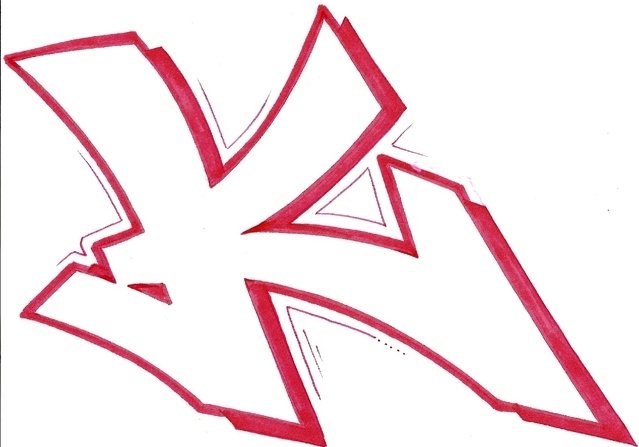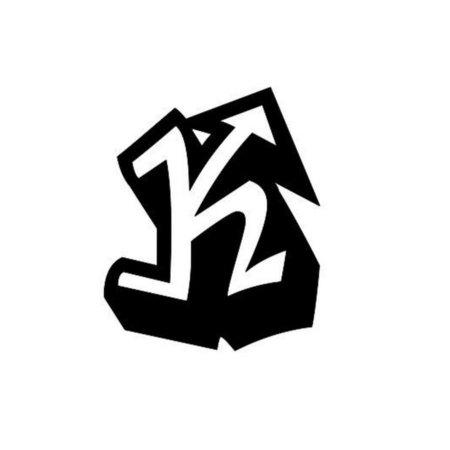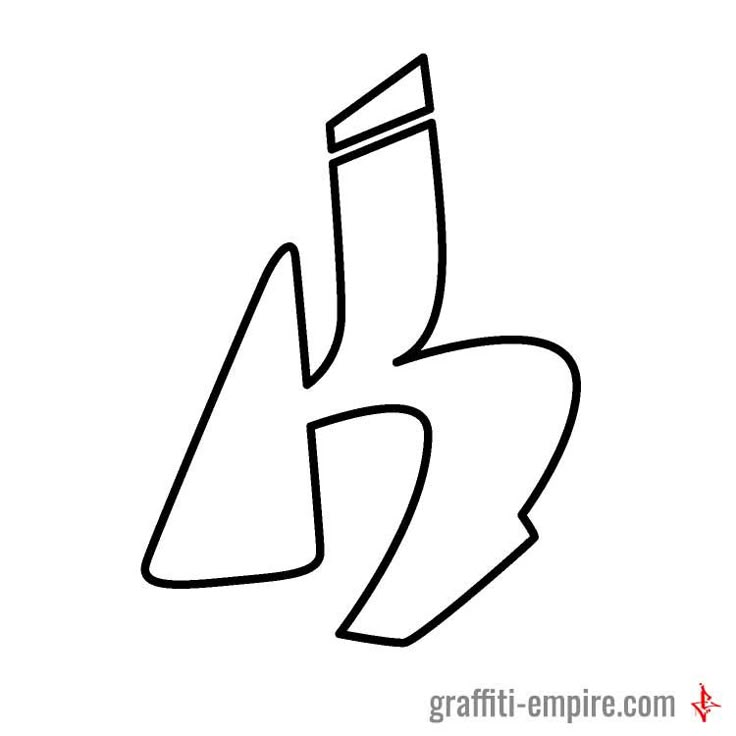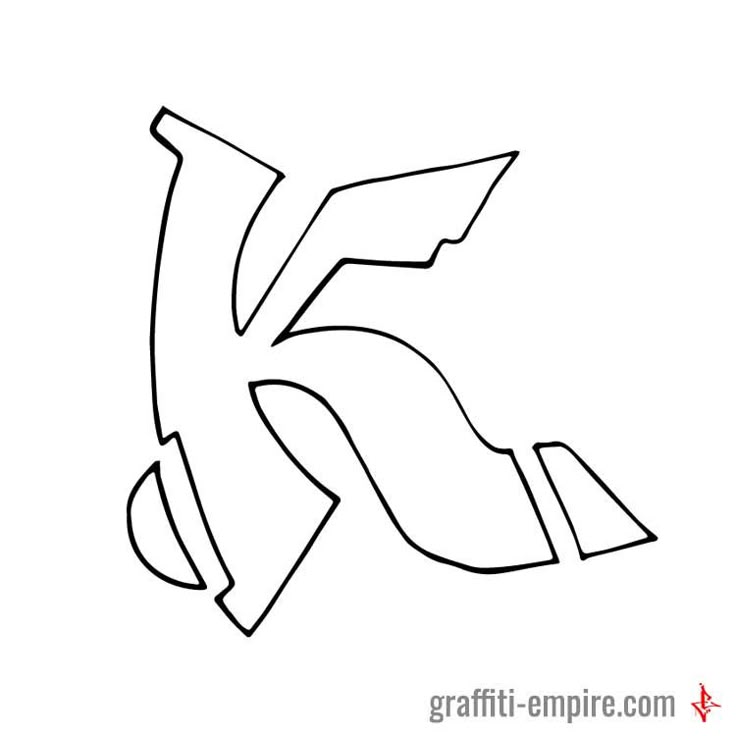
Классные картинки и рисунки буквы «К».
12 буква русского алфавита К — герой нашей сегодняшней подборки красивых картинок. Она встречается во многих словах, а в некоторых и по нескольку раз. Как и все остальные буквы в букваре, она требует тщательного изучения ребёнком, ведь пользоваться ей, он будет на протяжении всей жизни. Чтобы процесс обучения проходил легче, предлагаем в помощь карточки с буквой «К».
Пиксельный арт.
Буква в рамке.
Рисунок простым карандашом.
Карточка с буквой «К».
Срисовка для начинающих рисовать.
Вензель.
Весёлая буква «К».
В виде животного.
Жёлтая на красном фоне.
Граффити.
С глазками.
В огне.
В горошек.
Зелёная.
В золотом оформлении.
По клеточкам.
Мрачная буква.
Контурный рисунок.
Со светом.
С тенью.
В яркой короне.
Можно повторить простым карандашом.
В неоновом визуале.
Картинка в хорошем качестве.
Живая буква «К».
На фоне штриховки.
Чёрно-белая иллюстрация.
С узорами.
В разноцветном фоне.
Прикольный арт.
Рисуем по клеточкам.
Классный рисунок.
На коробке.
Картинка с буквой «К».
Маленькая картинка.
Жёлтая буква.
С огоньком
Каллиграфический почерк.
Срисовка для юных художников.
Учимся рисовать с объёмом.
Акварелью можно нарисовать что-то похожее.
Красивый рисунок.
Чёрная буква на белом фоне.
Из цветочков.
Крупным планом.
В тетрадном листе можно повторить синей ручкой.
Пытаемся украсить стандартное написание.
Граффити на стене.
Раскраска с буквой.
Маленькая и большая.
На уроке.
Буквица.
Пишем по точкам.
В свете прожекторов.
К в синем цвете.
С большими глазами.
С животным.
Для оформления.
Ч/Б.
Карточка с буквой для работы с ребёнком.
Красная.
С цветком.
В стиле поп-арт.
Контурный трафарет.
Обломки буквы.
Пишем синей ручкой.
«К» в стиле стрит-арт.
Буква светится в темноте.
С сердечками для влюблённых.
Из дерева.
В детский садик.
На урок в школу.
Объёмная буква.
Учимся рисовать вместе.
Современная картинка.
Красная буква для девочки.
Фото.
Из воздушного шарика.
На листе бумаги.
Карточка для учителя.
Для мальчика.
Повёрнутая буква «к».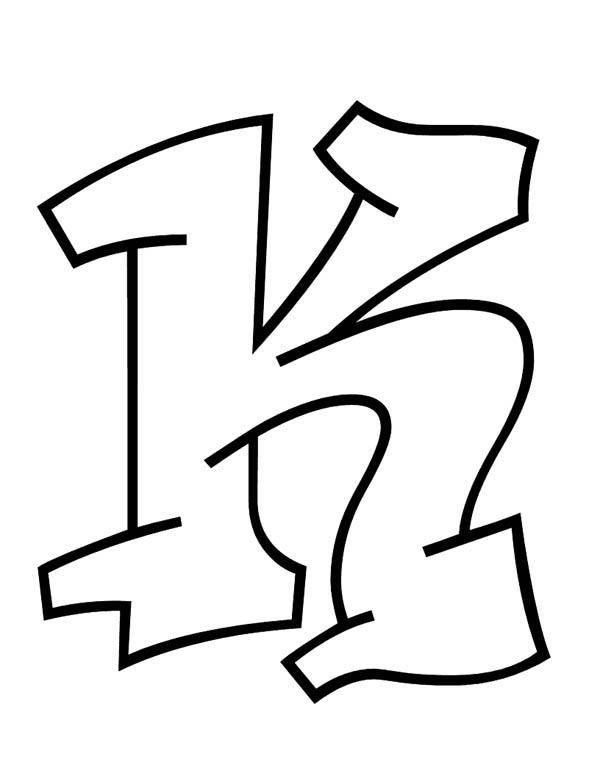
В низком разрешении.
Без фона.
С клубникой.
С бликами.
Компьютерная графика.
В геометрическом оформлении.
Коала.
Две буквы.
Нарисованная буквица.
Разноцветное изображение.
Фактурный рисунок.
Рисуем красками.
Можно раскрасить цветными карандашами.
Можно повторить, используя фломастеры.
Для обоев рабочего стола.
Для социальных сетей.
С иероглифами.
1) погребальные надписи: на надгробиях Фетиньи 1513 г., младенца-княжны Прасковьи Воротынской 1522 г.![]()
2) части погребальной надписи: на надгробии второй половины XVI в., надпись в нижней части плиты о «занятом месте», включавшая имя «МИХАИЛ», также нанесенная в технике граффито. На верхней части надгробия середины XVI в. вместо надписи вразброс вертикально и горизонтально процарапаны отдельные буквы;
.. НА АНДРЕЕВИЧА] РОСТОВСКОГО, на надгробии И.Д.Воронцова 1572 г. надпись: [И]ВАНЪ ДИМИТРЕЕВИ4 [В]ОРОнЦОВЪ.
Смысл нанесения пометок был, очевидно, таков: белокаменные плиты предлагались на продажу отесанные и орнаментированные, и, когда надгробие покупалось и принимался заказ на надпись, оно помечалось именем покойного или знаком мастера;
4) шифрованные знаки мастеров (тоже на боковых сторонах): на надгробии Ф.Ф. Юхнова 1585 г. у правого верхнего угла три знака: (по-видимому, личный знак мастера-камнерезца), на надгробии Ф.В. Яновой (Львовой) 1651 г. между арочками орнамента – косой крестик, в надписи на плите казначея Калинника 1664 г. между датой года и названием месяца – маленькая буква «фита» (возможно, цифра 9).
Буква K в стиле граффити